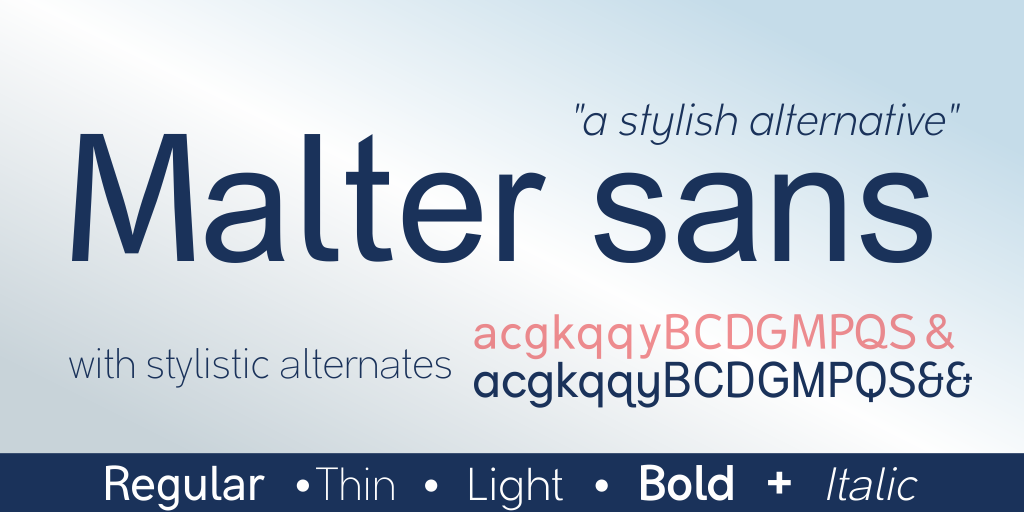
A Malter Sans é uma família de fontes sans-serif meticulosa e elegante projetada para criar ambientes de design gráfico modernos e envolventes. Compostas por linhas leves, espaçamentos precisos e formas simples, essa família de fontes oferece um equilíbrio perfeito entre funcionalidade e beleza. A Hamilton criou a Malter Sans com atenção aos detalhes em mente, resultando em uma linguagem tipográfica que se destaca como ideal para projetos comerciais modernos e sofisticados. Se você está procurando por uma fonte sans-serif para aplicar na sua próxima peça de design gráfico comercial, a Malter Sans pode ser a escolha perfeita para seu projeto. Para usuários finais que desejam experimentar a família de fontes, temos disponível uma demo limitada do modelo, com mais detalhes e informações sobre como usá-la disponíveis em www.studiotypo.com.